Bộ sưu tập font chữ miễn phí luôn là “kho vũ khí” quan trọng của dân thiết kế, từ làm logo, poster, bộ nhận diện thương hiệu đến nội dung mạng xã hội. Bài viết này tổng hợp hơn 50 font chữ đẹp, dễ ứng dụng, kèm gợi ý phong cách, trường hợp sử dụng và lưu ý bản quyền để bạn chọn đúng font cho từng dự án.
Top 50+ font chữ miễn phí đáng tải cho dân thiết kế
Nhóm font sans serif hiện đại, tối giản và dễ đọc
Sans serif là nhóm font không chân, có đường nét gọn gàng, phù hợp với hầu hết thiết kế hiện đại. Nếu bạn làm giao diện website, ứng dụng, poster công nghệ, hồ sơ năng lực, banner quảng cáo hoặc bài đăng mạng xã hội, đây là nhóm font nên có đầu tiên trong thư viện cá nhân.
– Montserrat: Font hình học nổi tiếng, nét chữ chắc, hiện đại, rất hợp cho tiêu đề, landing page, poster sự kiện và thiết kế thương hiệu trẻ trung.
– Poppins: Font sans serif bo tròn nhẹ, cân bằng giữa thân thiện và chuyên nghiệp, dùng tốt cho cả tiêu đề lẫn nội dung ngắn trong thiết kế digital.
– Inter: Font được tối ưu cho giao diện màn hình, độ đọc cao ở kích thước nhỏ, phù hợp cho UI design, dashboard, app mobile và website doanh nghiệp.
– Manrope: Font hiện đại, thoáng, có cảm giác công nghệ nhưng không quá lạnh, phù hợp với startup, fintech, SaaS, portfolio và slide thuyết trình.
– Work Sans: Font có nhịp chữ tự nhiên, dễ đọc, hợp cho nội dung dài trên website, brochure, proposal và các thiết kế cần vẻ nghiêm túc vừa phải.
– Sora: Font hình học có cá tính rõ, nét chữ vuông vức và hiện đại, thích hợp cho headline, thiết kế công nghệ, blockchain, AI, gaming hoặc sản phẩm số.
– Nunito: Font bo tròn mềm mại, thân thiện, phù hợp với giáo dục, trẻ em, ứng dụng chăm sóc sức khỏe, thương hiệu cộng đồng và thiết kế cần cảm giác gần gũi.
– Urbanist: Font tối giản, thời trang, thanh lịch, dùng tốt cho thương hiệu lifestyle, lookbook, poster thời trang, mỹ phẩm và các layout thiên về khoảng trắng.
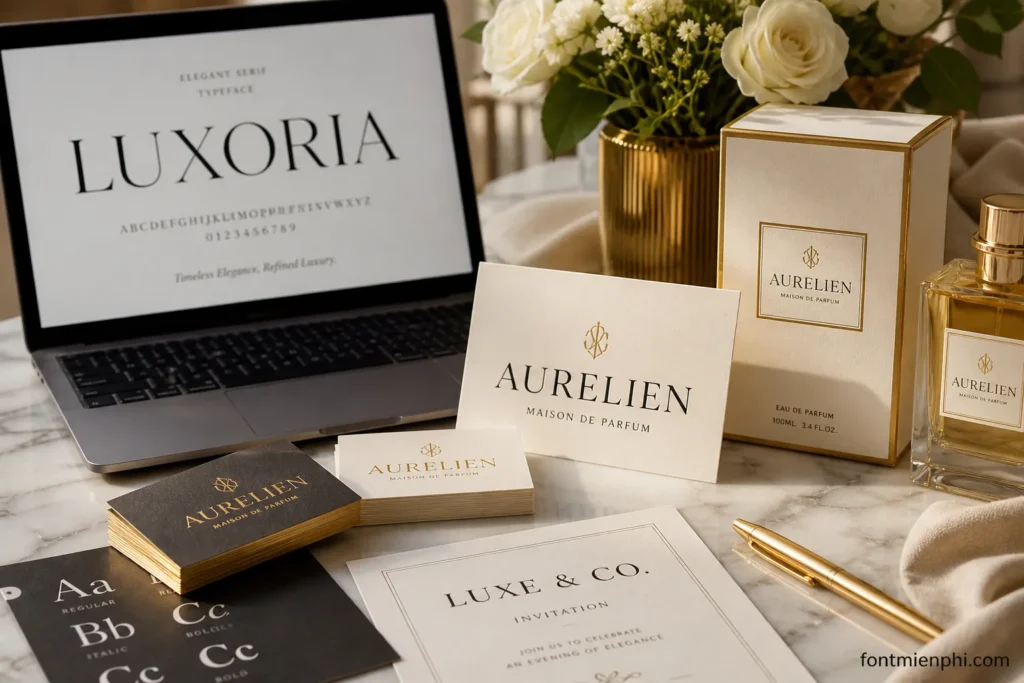
Nhóm font serif thanh lịch cho thương hiệu cao cấp
Serif là nhóm font có chân, thường gợi cảm giác cổ điển, sang trọng, đáng tin cậy và giàu chiều sâu. Khi thiết kế bao bì mỹ phẩm, thương hiệu thời trang, tạp chí, thiệp mời, menu nhà hàng cao cấp hoặc nhận diện cá nhân, serif giúp tác phẩm có chất editorial rõ rệt.
– Playfair Display: Font serif tương phản cao, đẹp ở kích thước lớn, rất hợp cho tiêu đề tạp chí, bộ nhận diện thời trang, mỹ phẩm và thương hiệu cao cấp.
– Cormorant Garamond: Font mang hơi hướng cổ điển, thanh mảnh, tinh tế, phù hợp với thiệp cưới, logo cá nhân, bìa sách, portfolio nghệ thuật và thiết kế editorial.
– Libre Baskerville: Font serif dễ đọc, có cảm giác học thuật và đáng tin cậy, thích hợp cho website chuyên gia, bài viết dài, báo cáo, catalogue và hồ sơ thương hiệu.
– Lora: Font serif mềm, hiện đại, có độ đọc tốt trên màn hình, phù hợp cho blog, tạp chí online, landing page dịch vụ tư vấn và nội dung kể chuyện thương hiệu.
– Merriweather: Font serif chắc chắn, tối ưu cho đọc dài, thích hợp cho bài viết chuyên sâu, website tin tức, sách điện tử và tài liệu thương hiệu cần sự nghiêm túc.
– Bodoni Moda: Font có độ tương phản mạnh, vẻ đẹp thời trang và kịch tính, dùng hiệu quả cho poster, lookbook, tiêu đề chiến dịch, logo boutique và bao bì cao cấp.
– Fraunces: Font serif có cá tính mềm mại, hơi vui mắt nhưng vẫn sang, phù hợp cho thương hiệu F&B, mỹ phẩm thủ công, bao bì quà tặng và thiết kế mang màu sắc hoài cổ.
– Prata: Font serif tối giản, đường nét sang trọng, dễ tạo điểm nhấn cho headline, bìa sách, banner sale cao cấp, website cá nhân và thiết kế phong cách luxury.
Nhóm font display nổi bật cho poster, logo và chiến dịch sáng tạo
Font display thường được dùng để tạo ấn tượng mạnh ở tiêu đề, logo, poster, thumbnail hoặc key visual. Nhóm này không nhất thiết phải dễ đọc ở đoạn dài, nhưng cần có cá tính rõ, giúp thiết kế khác biệt ngay từ cái nhìn đầu tiên.
– Bebas Neue: Font chữ cao, hẹp, mạnh mẽ, rất phổ biến trong poster, banner thể thao, thumbnail YouTube, tiêu đề chiến dịch và thiết kế cần sự dứt khoát.
– Anton: Font sans display đậm, nén vừa phải, tạo cảm giác chắc khỏe, phù hợp với headline quảng cáo, poster âm nhạc, sự kiện, sale campaign và layout mạng xã hội.
– Oswald: Font nén hiện đại, linh hoạt hơn Bebas Neue, dùng tốt cho tiêu đề website, infographic, poster, biển hiệu và thiết kế có nhiều lớp thông tin.
– Archivo Black: Font đậm, sắc nét, tạo độ phủ mạnh trên khung hình, phù hợp cho slogan, banner thương mại, thiết kế streetwear và các ấn phẩm cần độ “đập mắt”.
– Bungee: Font vui nhộn, có tinh thần đô thị, hợp với poster giải trí, quán cà phê trẻ, festival, sticker, bao bì snack hoặc dự án cần cảm giác năng động.
– Chivo: Font display có cấu trúc mạnh, khá nghiêm túc, phù hợp cho thương hiệu công nghệ, thiết kế sự kiện, tiêu đề báo cáo và poster mang tinh thần hiện đại.
– Thiết kế công nghệ và UI: Inter, JetBrains Mono, IBM Plex Mono, Fira Code, Source Code Pro, Space Mono.
– Thiết kế thiệp và handmade: Pacifico, Dancing Script, Great Vibes, Sacramento, Caveat, Kalam, Yellowtail.
Với các dự án cần tính nhất quán cao, hãy tạo sẵn một bộ font nền gồm một sans serif dễ đọc, một serif thanh lịch, một display nổi bật và một mono cho chi tiết kỹ thuật. Từ bộ nền này, bạn có thể mở rộng theo từng ngành hàng mà không phải bắt đầu lại từ đầu mỗi khi nhận brief mới.